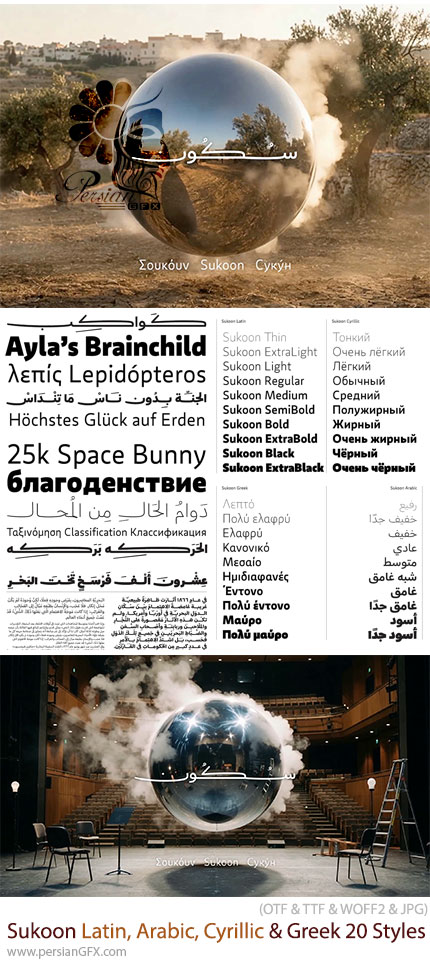
در این بخش شاهد فونت چندزبانه لاتین، عربی، سیریلیک و یونانی سکون با 20 استایل متنوع می باشید که با فرمت های TTF و OTF و WOFF2 و JPG بر روی سایت برای دانلود قرار گرفته است. Sukoon Latin, Arabic, Cyrillic & Greek 20 Styles + Variable یک خانواده فونت حرفهای و چندزبانه است که از زبانهای لاتین، عربی، سیریلیک و یونانی پشتیبانی میکند. این مجموعه با طراحی مدرن و انعطافپذیر، شامل 20 وزن و استایل مختلف به همراه نسخه Variable Font بوده و گزینهای ایدهآل برای پروژههای برندینگ، طراحی رابط کاربری، تبلیغات، نشر و تولید محتوای دیجیتال محسوب میشود. فونت Sukoon با ترکیب فرمهای خوانا، ساختار متعادل و ظاهر حرفهای، امکان استفاده در پروژههایی با زبانهای مختلف را فراهم میکند و برای طراحیهای بینالمللی بسیار کاربردی است. Sukoon Font Family یک فونت حرفهای، مدرن و چندمنظوره با پشتیبانی از چهار سیستم نوشتاری مهم است. وجود 20 استایل مختلف و نسخه Variable Font باعث شده این خانواده فونت برای طیف گستردهای از پروژههای خلاقانه، از طراحی لوگو و برندینگ گرفته تا رابط کاربری و تبلیغات، انتخابی قدرتمند و انعطافپذیر باشد.
مناسب برای:
- طراحی لوگو و هویت بصری برند
- طراحی بستهبندی محصولات
- پوستر و تبلیغات
- طراحی مجلات و کتابها
- رابط کاربری وب و اپلیکیشن (UI/UX)
- طراحی شبکههای اجتماعی
- تیترهای تبلیغاتی
- طراحی ارائهها و پرزنتیشنها
- پروژههای چندزبانه بینالمللی
قابلیت Variable Font
نسخه Variable این فونت به طراح اجازه میدهد کنترل بیشتری روی ظاهر تایپوگرافی داشته باشد:
- تنظیم دقیق ضخامت حروف
- ایجاد سبکهای متنوع بدون نیاز به نصب فایلهای متعدد
- انعطاف بیشتر در طراحی دیجیتال
- مناسب برای وب و نرمافزارهای مدرن طراحی
پشتیبانی چندزبانه حرفهای
یکی از ویژگیهای مهم Sukoon، پشتیبانی همزمان از چند سیستم نوشتاری است که آن را برای پروژههای جهانی مناسب میکند. طراحان میتوانند یک هویت بصری یکپارچه برای زبانهای مختلف ایجاد کنند.
مناسب برای:
- طراحان گرافیک
- طراحان برندینگ
- طراحان UI/UX
- طراحان وب
- آژانسهای تبلیغاتی
- طراحان چاپ و نشر
- تولیدکنندگان محتوا
- تایپوگرافیستها